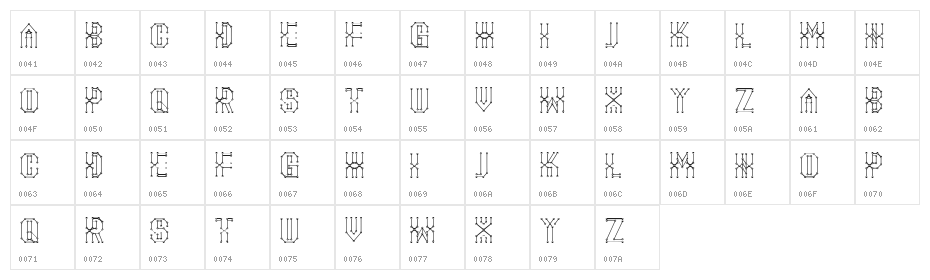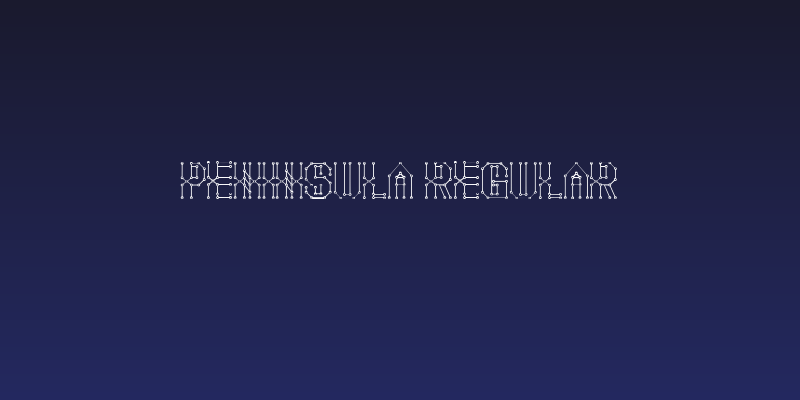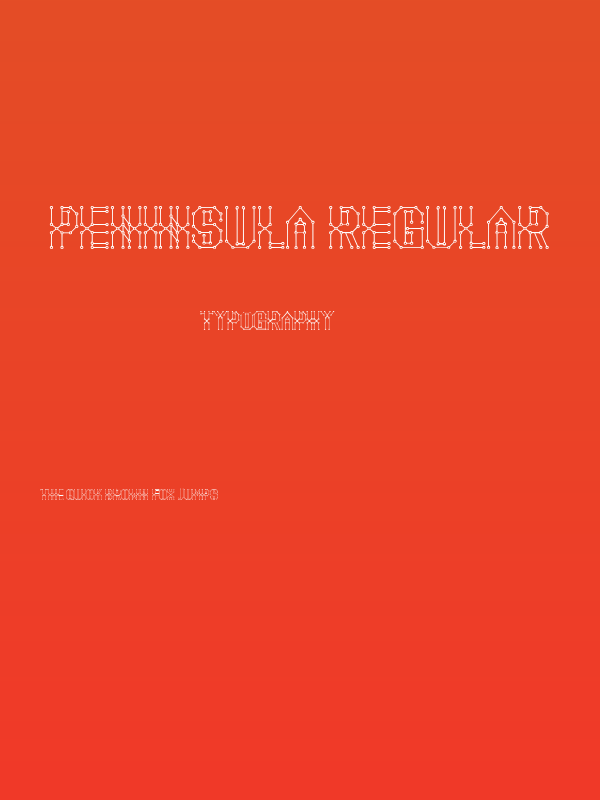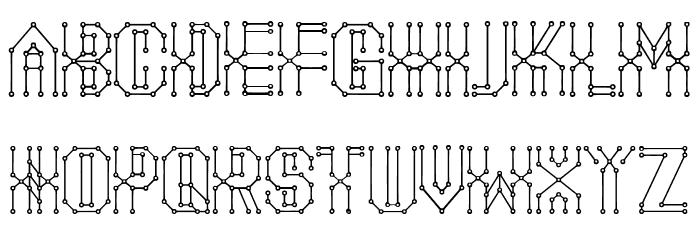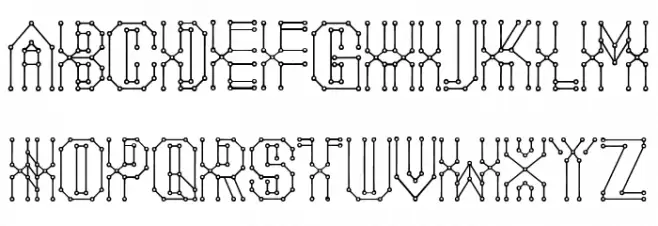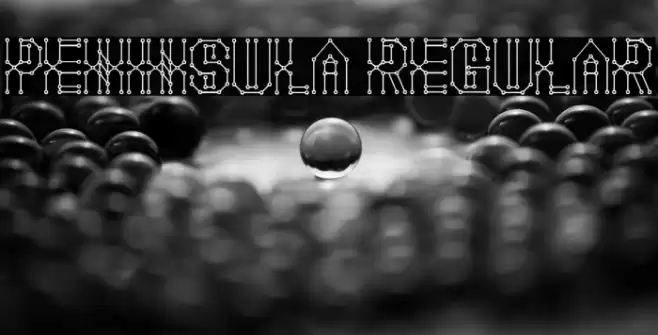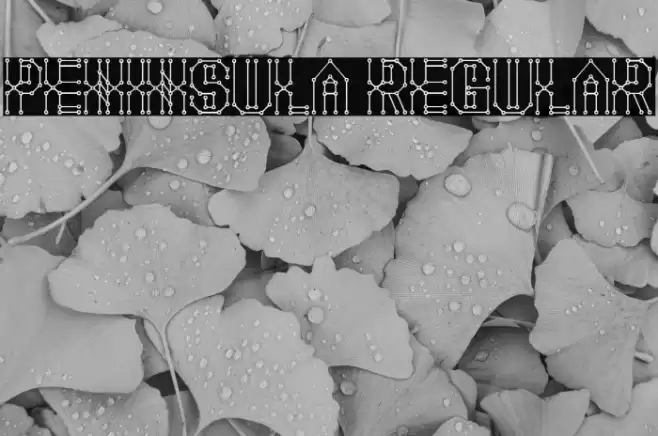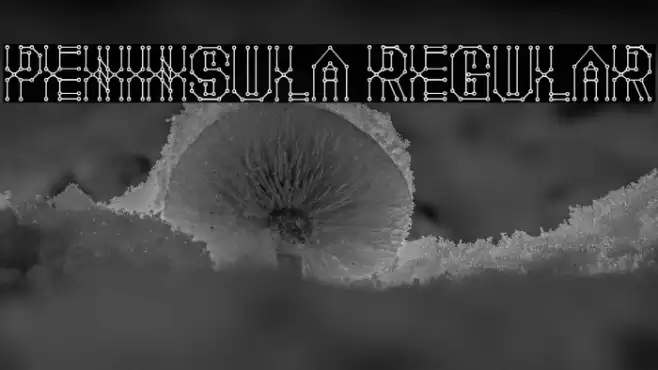
Peninsula Regular Font
| Progetti proposti | Ideal for tech-themed posters, digital artwork, branding for technology companies, or any project needing a futuristic touch. |